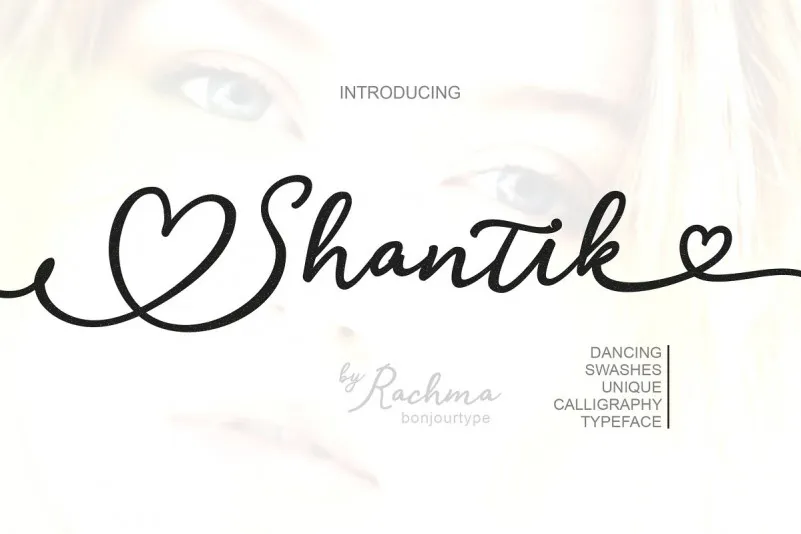
Shantik Script Font – Fonte Grátis
Shantik Script Font
A Shantik Font é uma escolha perfeita para aqueles que buscam uma fonte realista e escrita à mão para projetos digitais. Esta elegante e contemporânea fonte script foi criada por 24Design, com um design fluido e limpo que parece natural e confiável ao usar. Ideal tanto para assinaturas quanto para criações de design gráfico, a Shantik é perfeita quando você quer uma aparência descomplicada sem precisar de um estilo muito estrito. Composto de elementos simples e claros, a Shantik possui uma harmonia natural que torna-a versátil em diversas aplicações. Seja para criar um visual sofisticado e elegante ou para adicionar um toque único a seu design digital, essa fonte é certamente algo que você vai querer no seu arsenal. É perfeitamente adaptável para diferentes contextos de uso sem perder sua essência única, tornando-a uma escolha valiosa para designers e criativos em busca de uma solução conveniente e elegante.